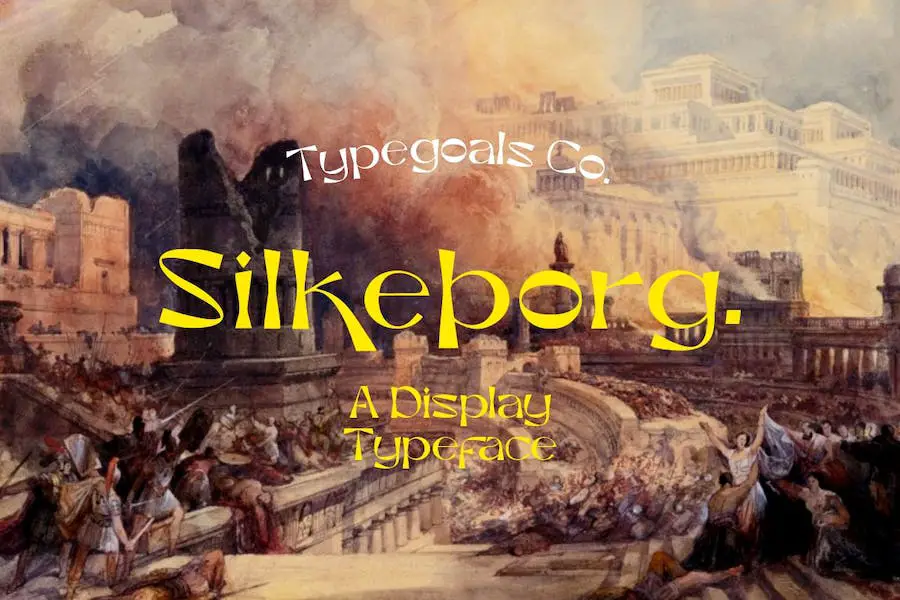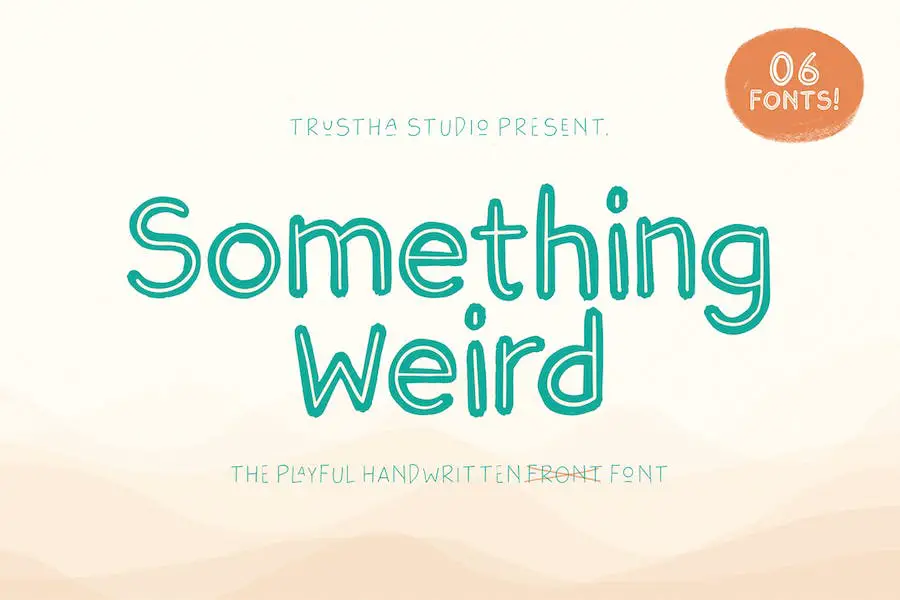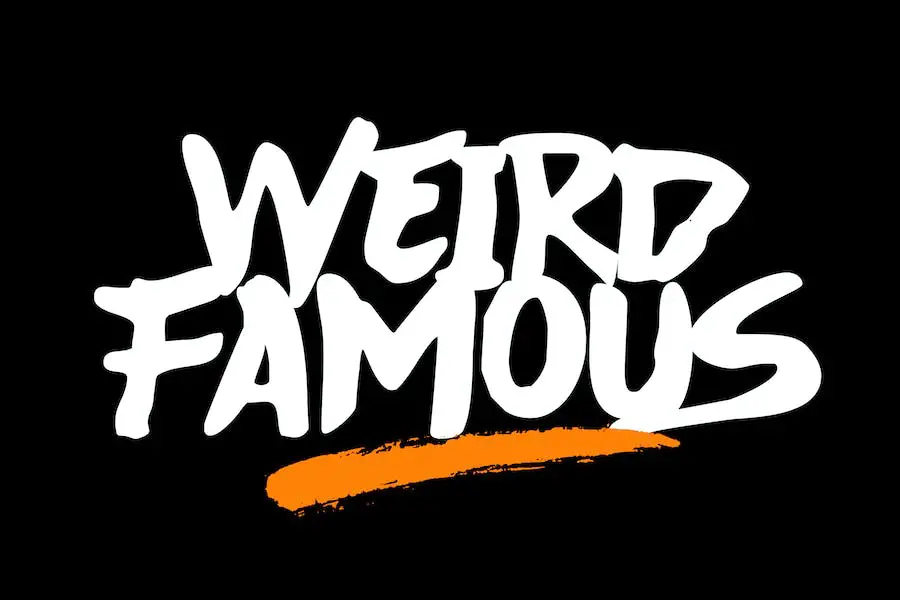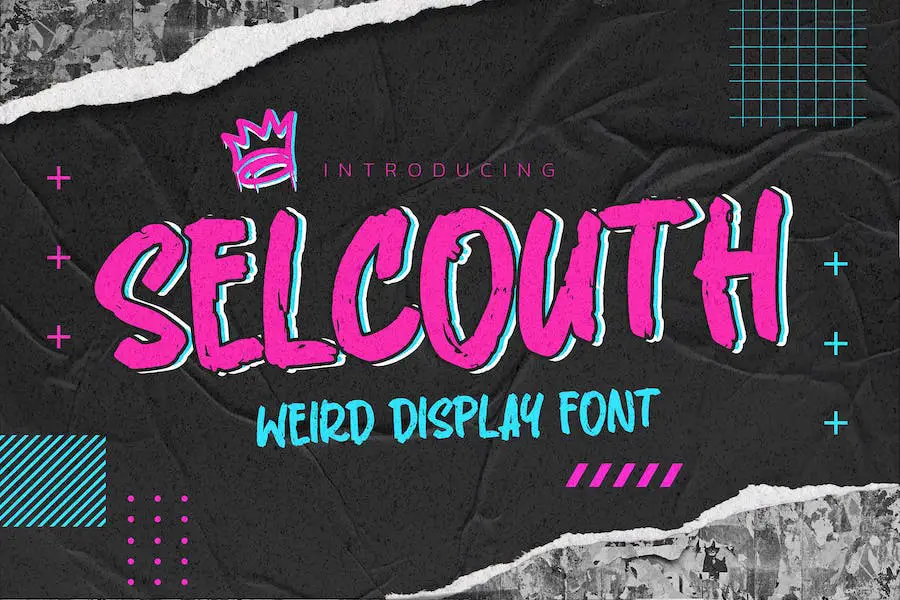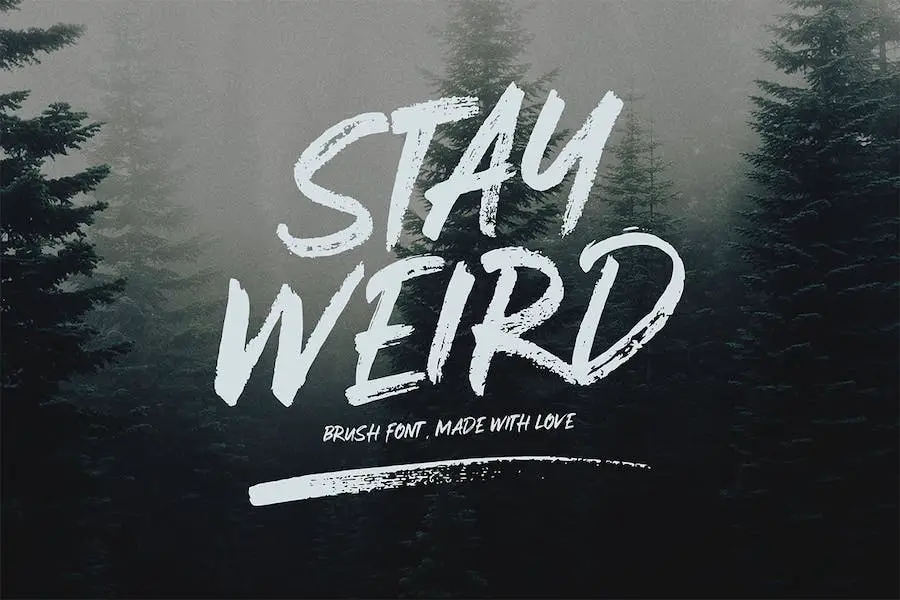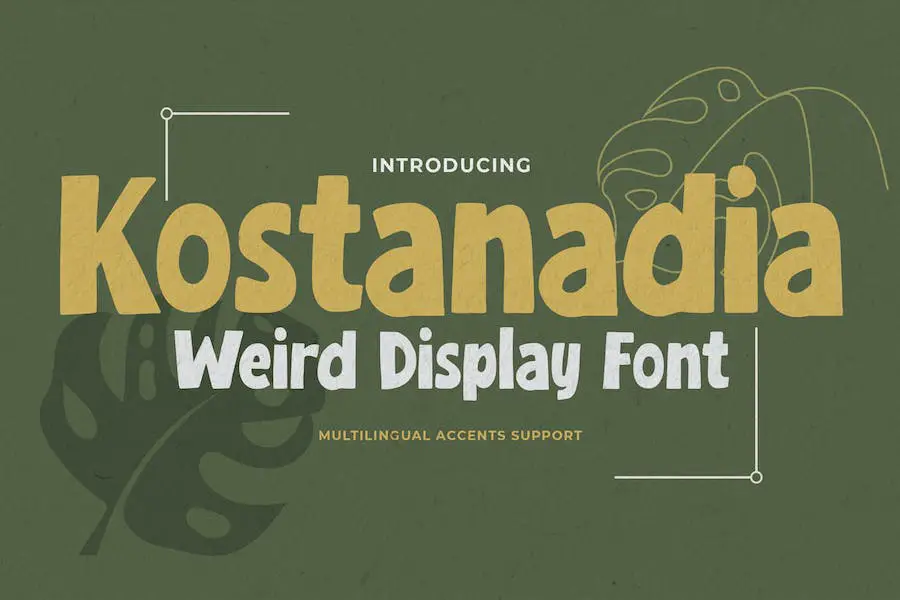
Tuttoz
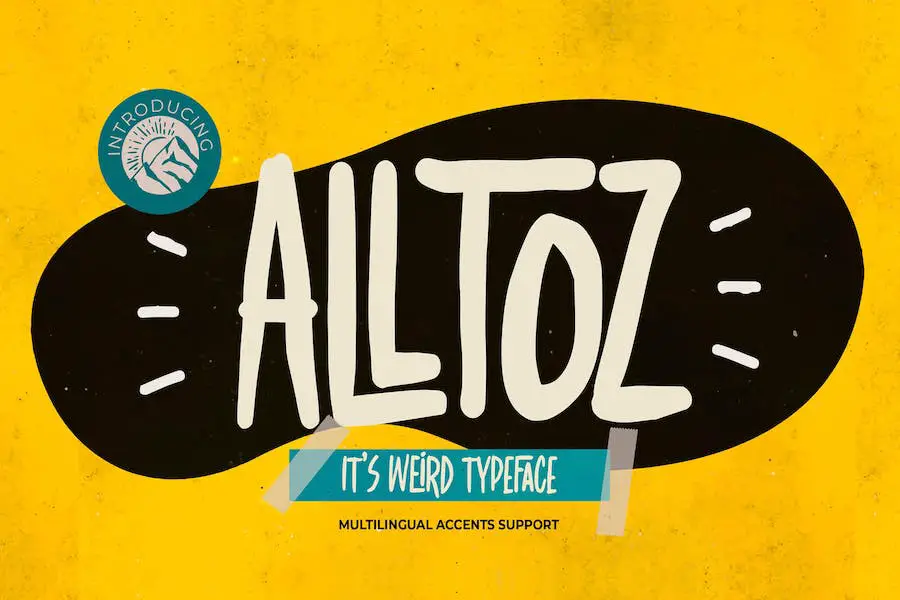
Alltoz è un font moderno e strano chiamato "It" che aggiunge un tocco naturale disegnato a mano ai tuoi progetti. Con il suo bel tocco naturale e l'attenzione ai dettagli, questo carattere è perfetto per una vasta gamma di progetti di design tra cui inviti, loghi, copertine di libri, artigianato e altro ancora.
Può anche essere utilizzato per sovrapposizioni fotografiche, cartelli, vetrine, album di ritagli e tag. Il carattere è codificato PUA, consentendoti di accedere a tutte le sue legature e glifi.
Con il suo stile autentico e di classe, Alltoz è ottimo anche per la filigrana fotografica, loghi e branding, pubblicità, design di prodotti, cancelleria, design di matrimoni, etichette, confezioni di prodotti ed eventi speciali.
Se stai cercando di aggiungere un tocco di calligrafia ai tuoi progetti, Alltoz è la scelta perfetta.
Strano Melone
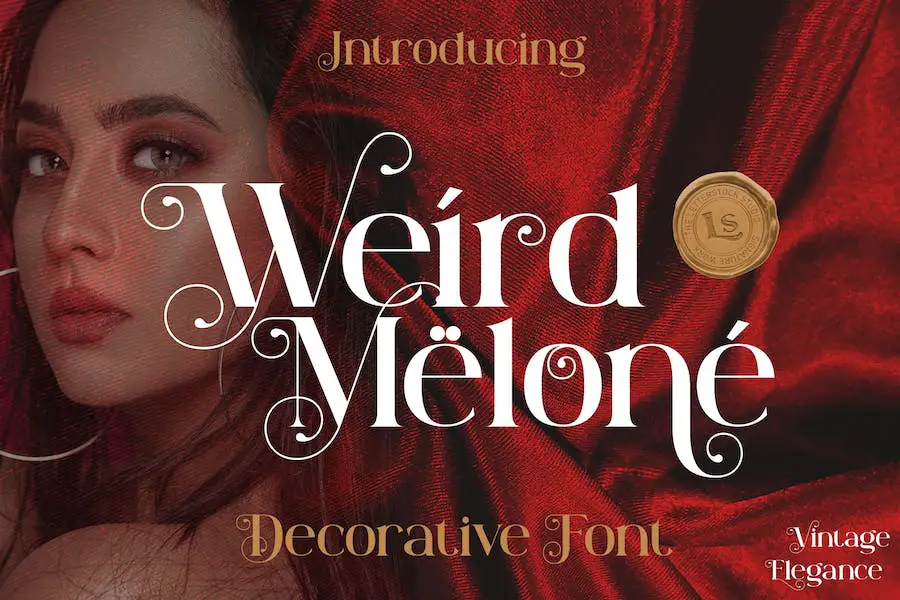
Weird Melone è un font moderno e strano, perfetto per i grafici che cercano di aggiungere un tocco unico ai loro progetti. Con il suo set di 228 caratteri e le funzionalità Opentype, questo font offre infinite possibilità per la pubblicità, il design del logo, le etichette, la confezione del prodotto, gli inviti e altro ancora.
Ispirato ai poster di film retrò avvistati in una caffetteria locale, Weird Melone è stato meticolosamente realizzato a mano per catturare un'estetica naturale e fatta a mano. Le linee pulite ottenute attraverso l'uso di strumenti penna conferiscono a questo carattere un aspetto raffinato che può migliorare l'identità di qualsiasi marchio.
Che tu stia lavorando a un progetto professionale o semplicemente cercando di ravvivare i tuoi progetti personali, Weird Melone è un font che farà sicuramente una dichiarazione. Il suo stile non convenzionale attirerà sicuramente l'attenzione e lascerà un'impressione duratura.
Immagine
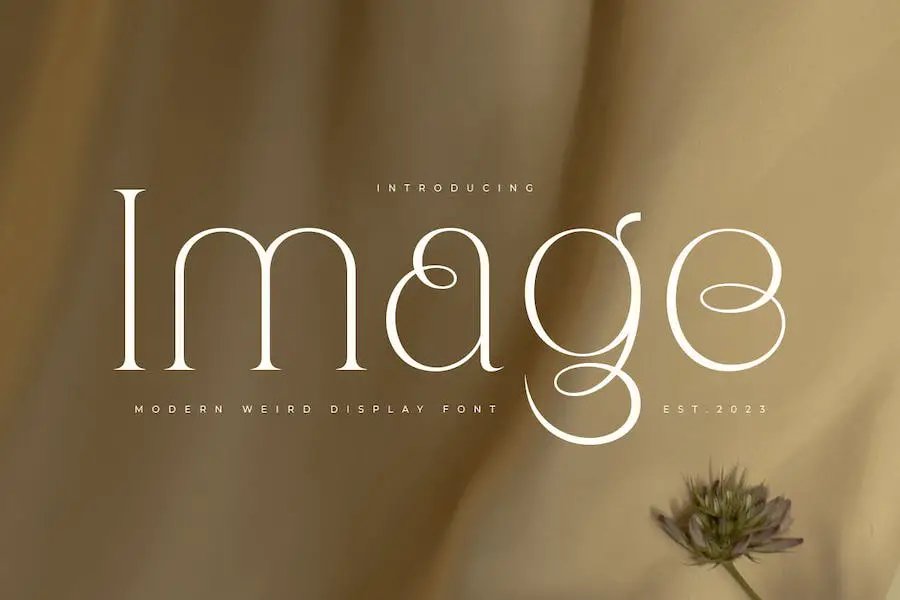
L'immagine è un notevole font Modern Weird Luxury che è stato creato appositamente per sofisticati scopi di branding. Con le sue forme distintive e l'estetica elegante, aggiunge un valore immenso all'identità visiva del tuo marchio.
Che tu sia un designer o un product owner, questo font è la soluzione perfetta per esaltare lo stile e la modernità dei tuoi design. L'ampia gamma di caratteri forniti con questo font ti consente di creare variazioni illimitate che soddisfano le tue esigenze creative.
Dì addio alla tipografia ordinaria e dai il benvenuto allo straordinario con Image. Ideale per gli appassionati di font moderni e strani e compatibile con Figma, questo font apre nuove possibilità per i tuoi progetti di design. Aggiorna i tuoi sforzi di branding e fai un'impressione duratura con Image.
Pandora
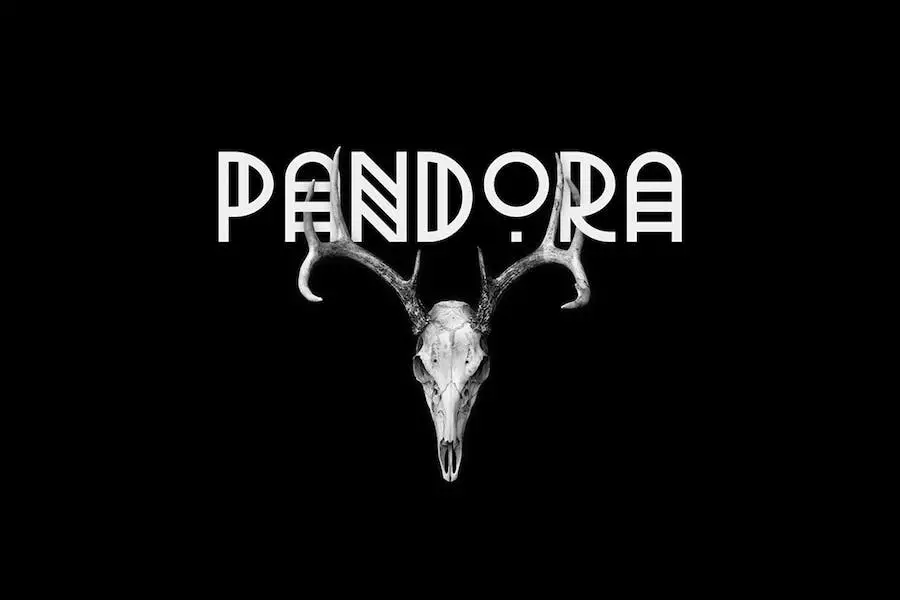
Pandora è un carattere strano e moderno che eleverà i tuoi progetti di design a un livello completamente nuovo. Con i suoi tre caratteri unici e distintivi, offre infinite possibilità di espressione creativa.
La prima variante, Ep.1, presenta un design pulito e semplice, perfetto per aggiungere un tocco di stravaganza ai tuoi progetti. Ep.2 fa un ulteriore passo avanti con i suoi elementi geometrici, aggiungendo un tocco astratto e intrigante. E se stai cercando di spingerti veramente oltre i limiti, l'Ep.3 è il font che fa per te: è fuori dal mondo!